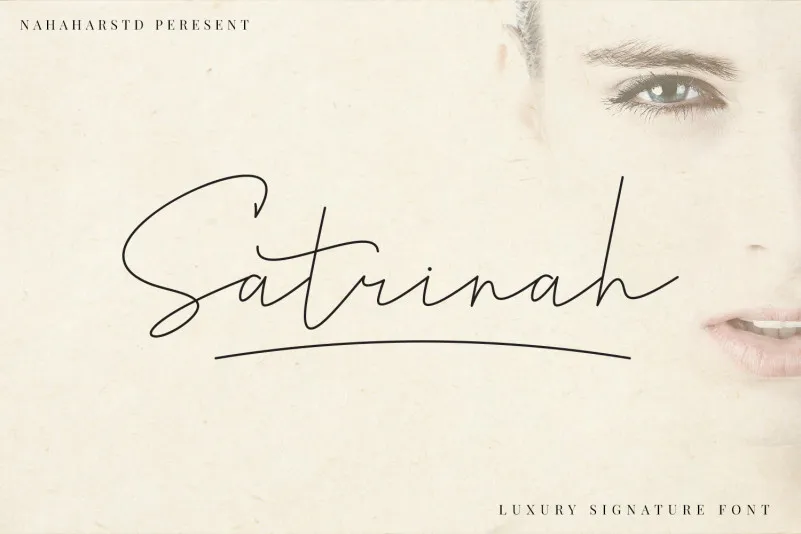
Satrinah – Signature Font – Download Grátis
A Satrinah Signature Font é uma elegante tipografia para assinatura perfeita para projetos diversos no design. Suavemente escrita por mãos humanas, ela proporciona um toque de requinte e delicadeza a qualquer projeto que escolha usá-la. Ideal tanto para criações de logomarca, como para design de embalagens de produtos ou até mesmo para artesanato em mugs. Seja você criando rótulos de alimentos gourmet, ou desenhando cartões de convite personalizados para sua próxima festa casamenteira, a Satrinah Signature Font vai fazer seu trabalho bem feito. Além disso, ela também é perfeita para criar capas de livros com uma caligrafia delicada que encoraja leitores a mergulharem em cada página, seja você um designer de capa ou simplesmente querendo criar uma sensação única no seu livro. Na área das redes sociais e publicações digitais, ela pode ser usada para adicionar um toque agradável ao texto dos seus posts ou mensagens, ou até mesmo como fundo para fotos em sua foto de perfil. Sem dúvida, é uma fonte que vai tornar qualquer projeto mais bonito e sofisticado.